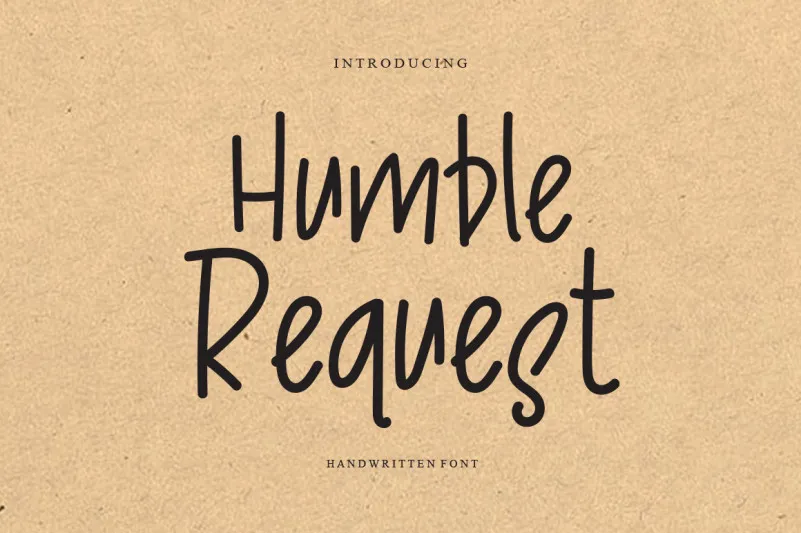
Aqui está uma versão adaptada das instruções fornecidas para criar descrição de 2 parágrafos curtos para a página de download da fonte “Humble Request Font”: Esta é uma fonte escrita à mão única, divertida e amigável. Seja você um criador entusiasmado buscando uma fonte para Instagram ou alguém que está trabalhando em um projeto DIY e precisa de um traçado calligráfico personalizado, esta font pode transformar sua ideia mais original em obra-prima artística. Humble Request Font é perfeita tanto para aqueles que desejam uma mão-douriada e pessoal quanto para quem busca a elegância da escrita à mão. Essencialmente versátil, ela se adapta a diversos projetos digitais – seja para criar um logo inovador ou personalizar mensagens no Facebook. A fonte de levincreative não só reúne as características únicas e divertidas que foram apontadas na descrição original em inglês, mas também oferece uma vasta gama de opções para qualquer criatividade que você possa ter. Com a Humble Request Font, suas ideias mais inspiradoras ganham vida, tornando-as verdadeiras obras-primas de arte digital. Essa fonte escrita à mão é ideal tanto para iniciantes quanto para profissionais, proporcionando uma mistura perfeita entre seriedade e personalidade que define o estilo da levincreative. Não se esqueça de experimentar a diversão e a criatividade desta fonte para transformar seu próximo projeto digital em algo realmente especial.